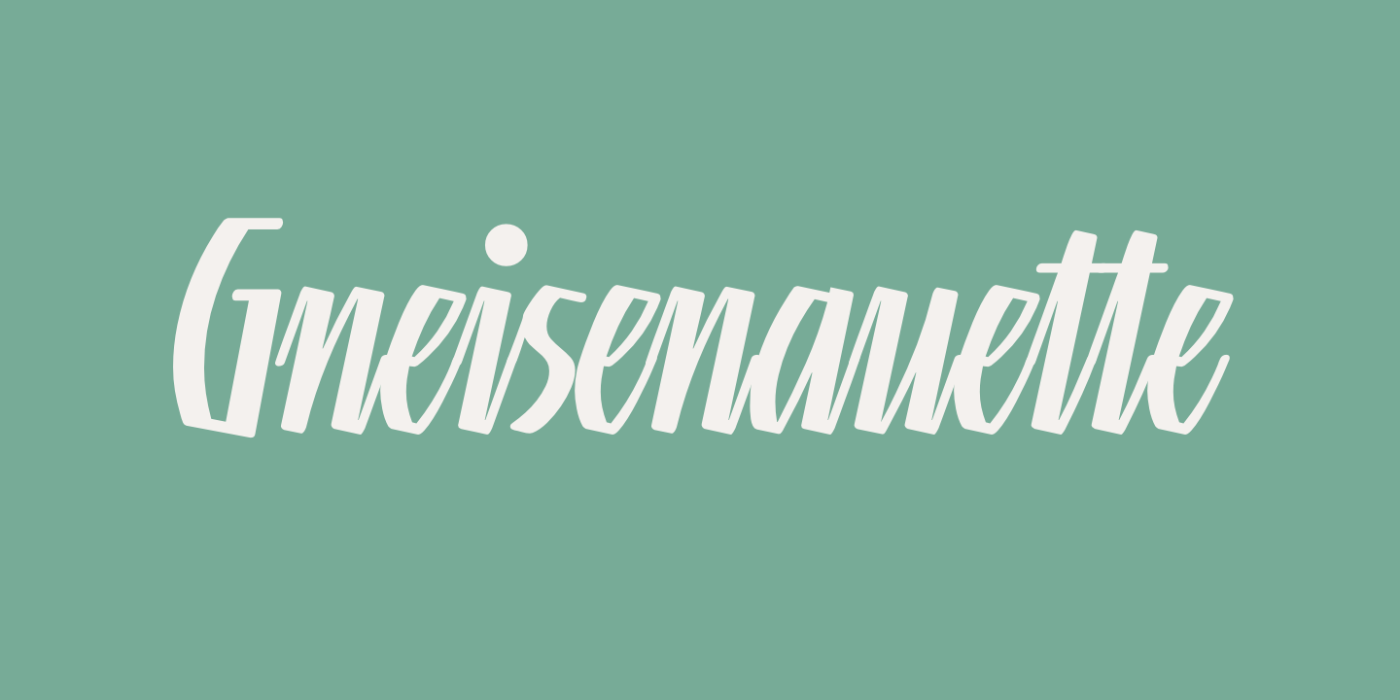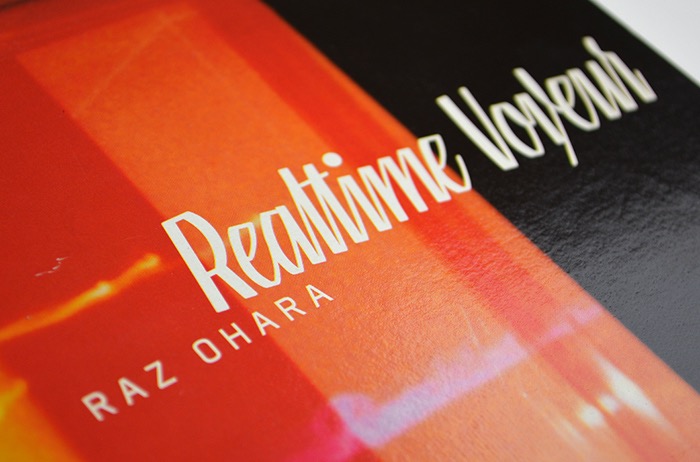
- 1997
- Antiqua Schreibschrift
Die Linotype Gneisenauette wurde im Rahmen eines Schriftenwettbewerbes in die Take Type Library von Linotype aufgenommen. Gestaltet hat die schildermalerartige Schreibschrift der lettische Designer Gustavs A. Grinbergs. Die Schrift ist in 4 Strichstärken ausgebaut und für jeden der Schnitte gibt es eine Alternativ-Version mit Schwungbuchstaben.
Anwendung auf einem Plattencover. (Foto F. Hardwig, CC BY 3.0)